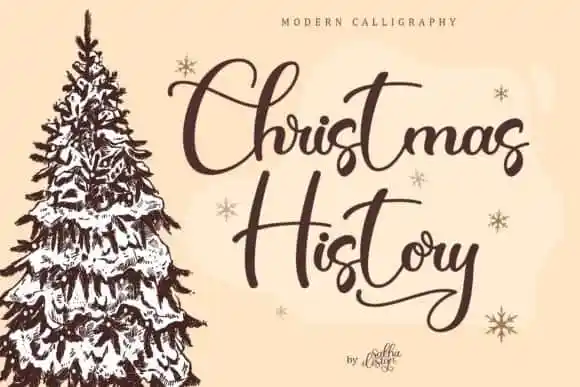
Christmas History Calligraphy Font – Download Grátis
A fonte ‘Christmas History Calligraphy Font’ é uma elegante fonte cíliada perfeita para a estação natalina. Inspirada na arte manual do passado, ela traz uma mistura de sofisticação e frescura ao seu design, com suas curvas delicadas e detalhes que se tornam ainda mais belos quando são usados em alta resolução. Esta fonte é ideal para criar cartões natalinos românticos ou qualquer projeto onde você deseja adicionar um toque especial. Ela oferece uma variedade de elementos únicos como alternativas de caracteres e ligaduras, tornando cada obra que você cria única e marcante. Talvez não seja tão comum encontrar uma fonte natalina tão elaborada e sofisticada em uma fonte cíliada, mas isso apenas a torna mais especial. Seja para decorar cartões de Natal ou criar um calendário encantador, este design vai dar aquele toque final perfeito à sua produção. O designer responsável, Sakha Design, trouxe uma experiência de uso única e acessível que combina prazer visual com facilidade operacional. Com certeza é a fonte natalina perfeita para quem ama decoração natalina ou simplesmente busca algo único para suas produções gráficas.